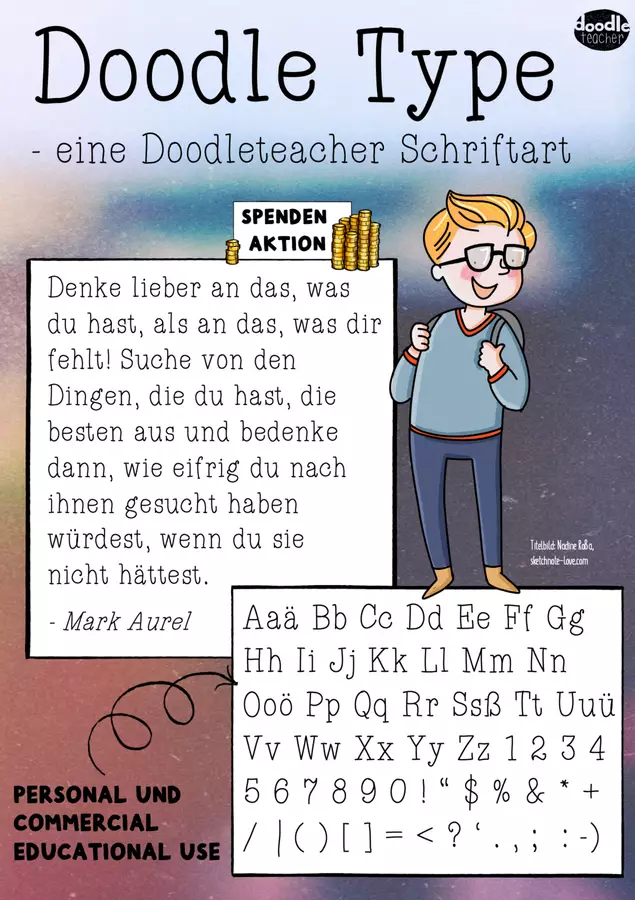
Eine sehr schöne und einfache Schriftart die an einer Type ähnlichen Schrift angelegt etwas freier und doodeliger arrangiert wurde. Gibt es auch im PAKET!